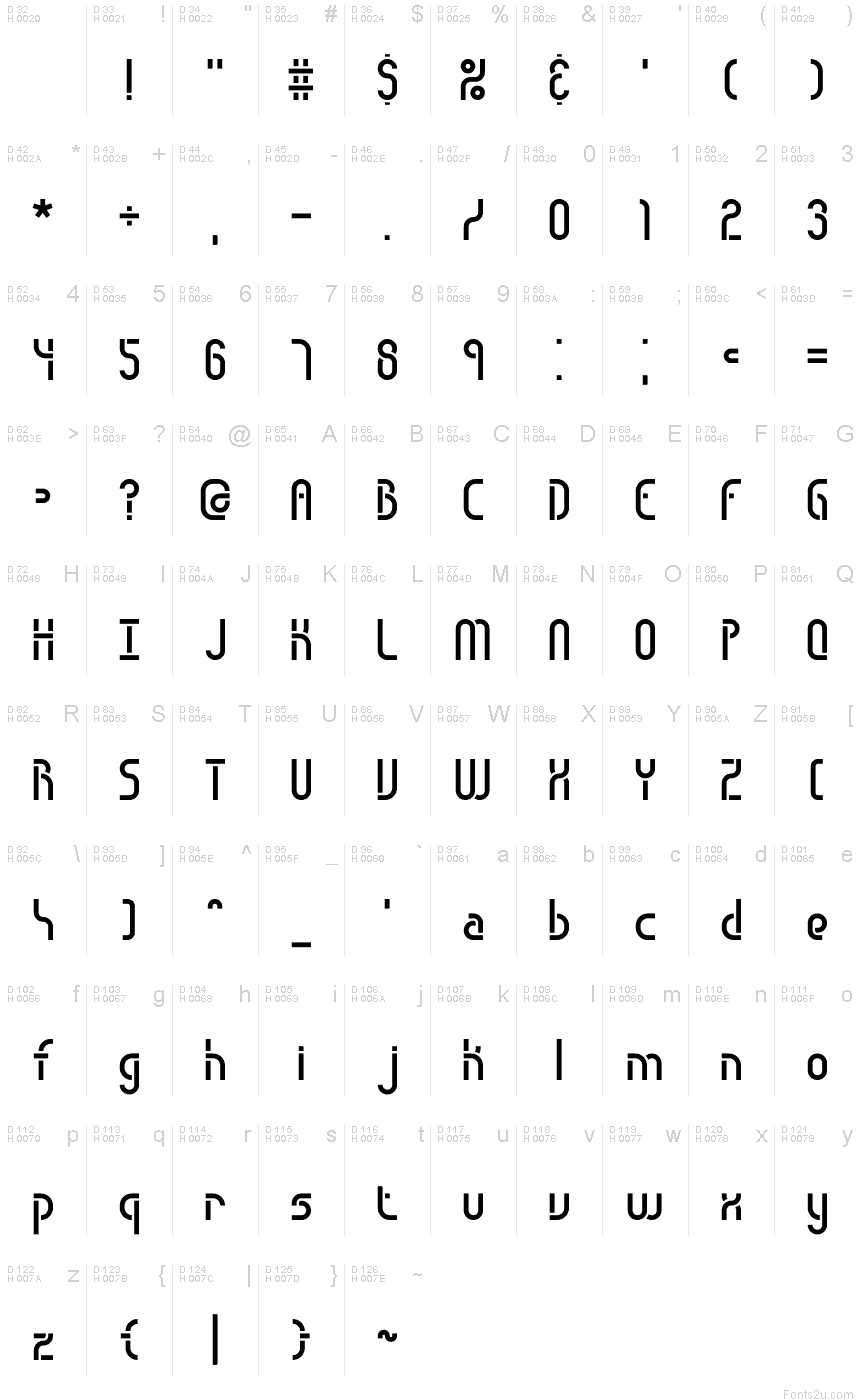
Obstacle BRK
Obstacle autorstwa ÆNIGMA FONTS to darmowy retro krój ekspozycyjny, zbudowany z szerokich, w większości jednolitych kresek i zaokrąglonych form geometrycznych. Jego niskie, modularne litery łączą gładkie łuki z kanciastymi połączeniami i nagłymi przerwami, przywodząc na myśl wczesne napisy komputerowe i futurystyczne oznakowanie.
Grafika cyfrowa to naturalne środowisko dla tego zwartego, mechanicznego stylu, szczególnie w przypadku menu gier i wizualizacji muzycznych. Sprawdzi się także na plakatach imprezowych oraz w brandingu technologicznym. W grafikach interfejsów połamane kreski mogą stać się częścią przycisków, ścieżek lub obramowań przypominających obwody, zamiast pełnić funkcję neutralnego tekstu.